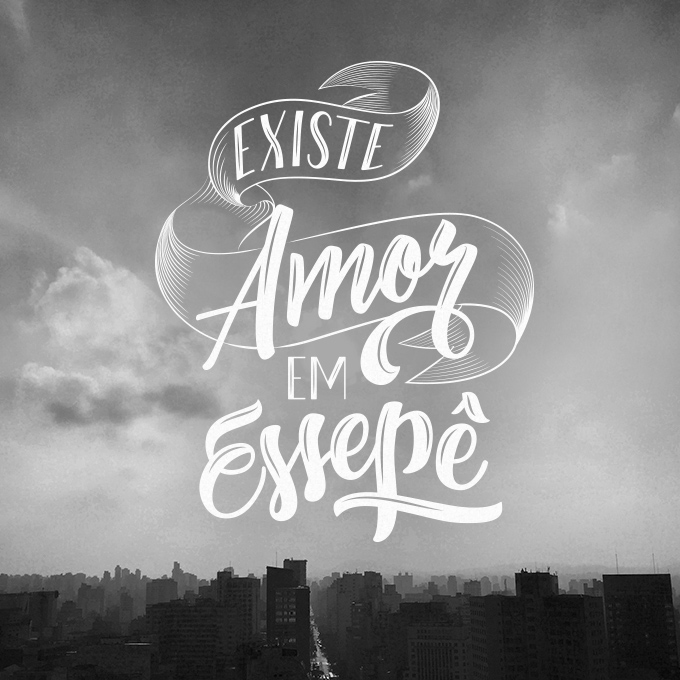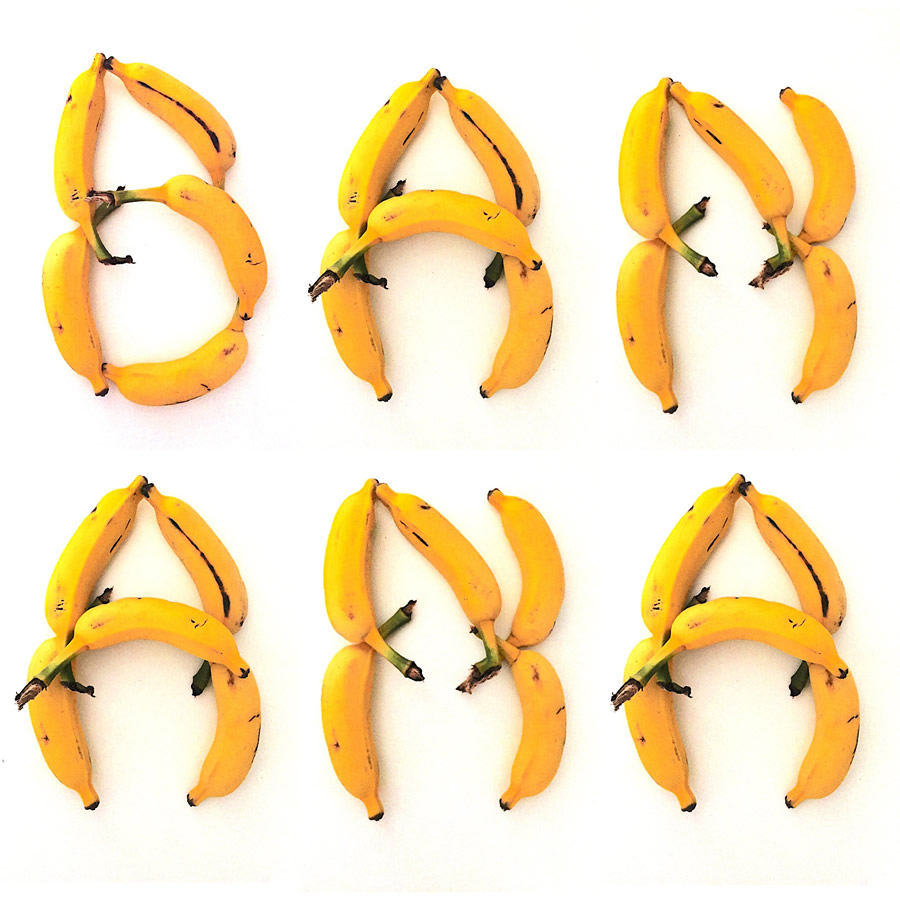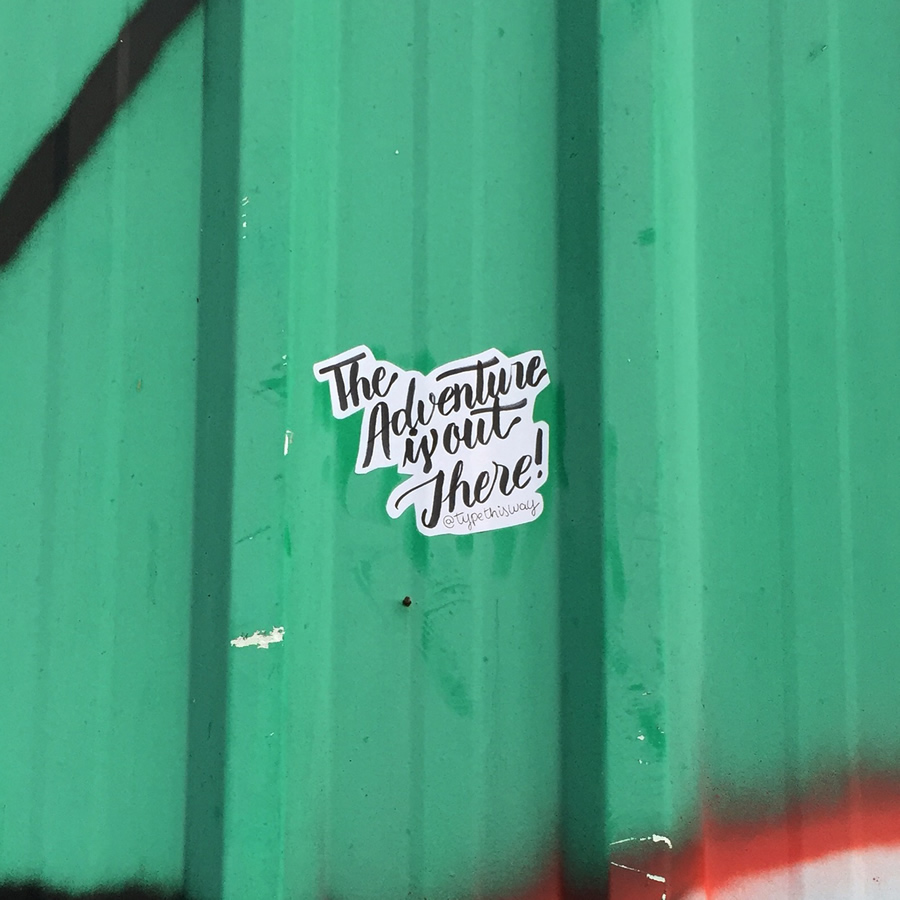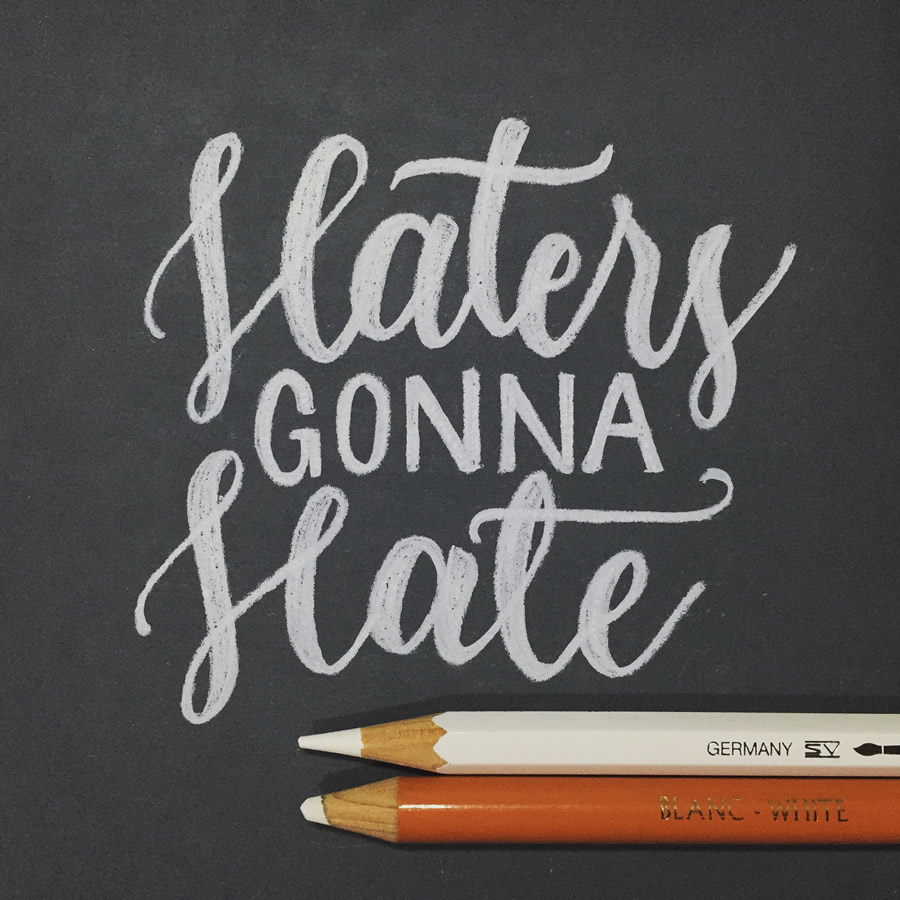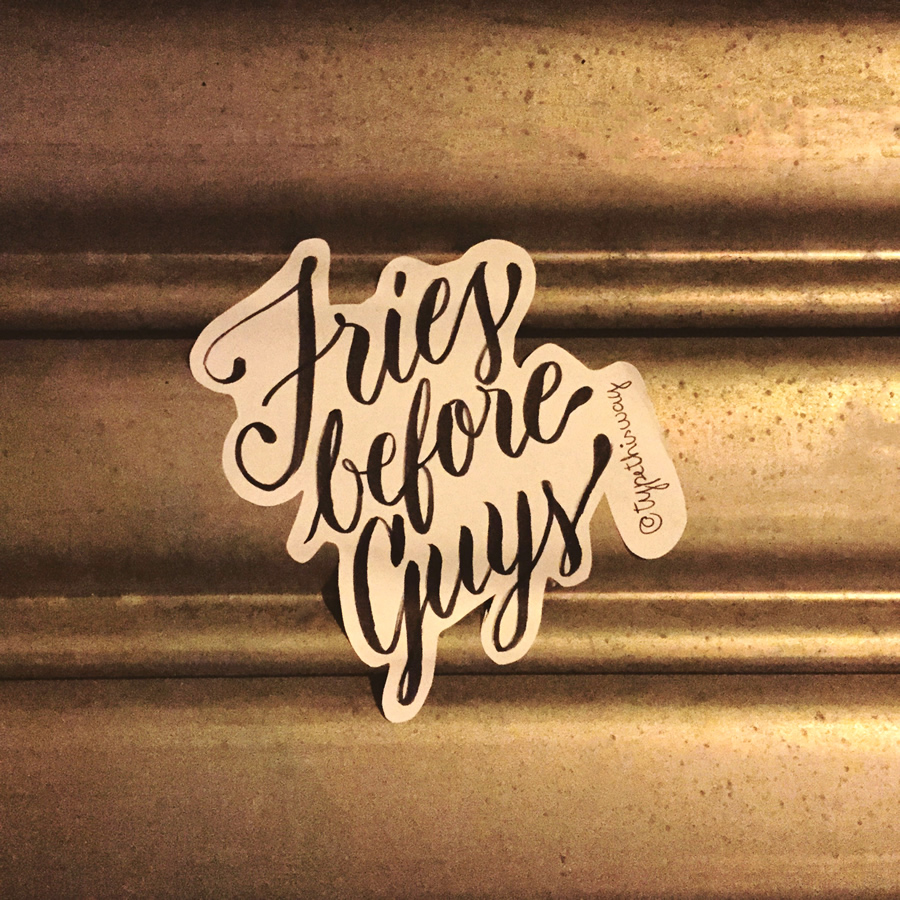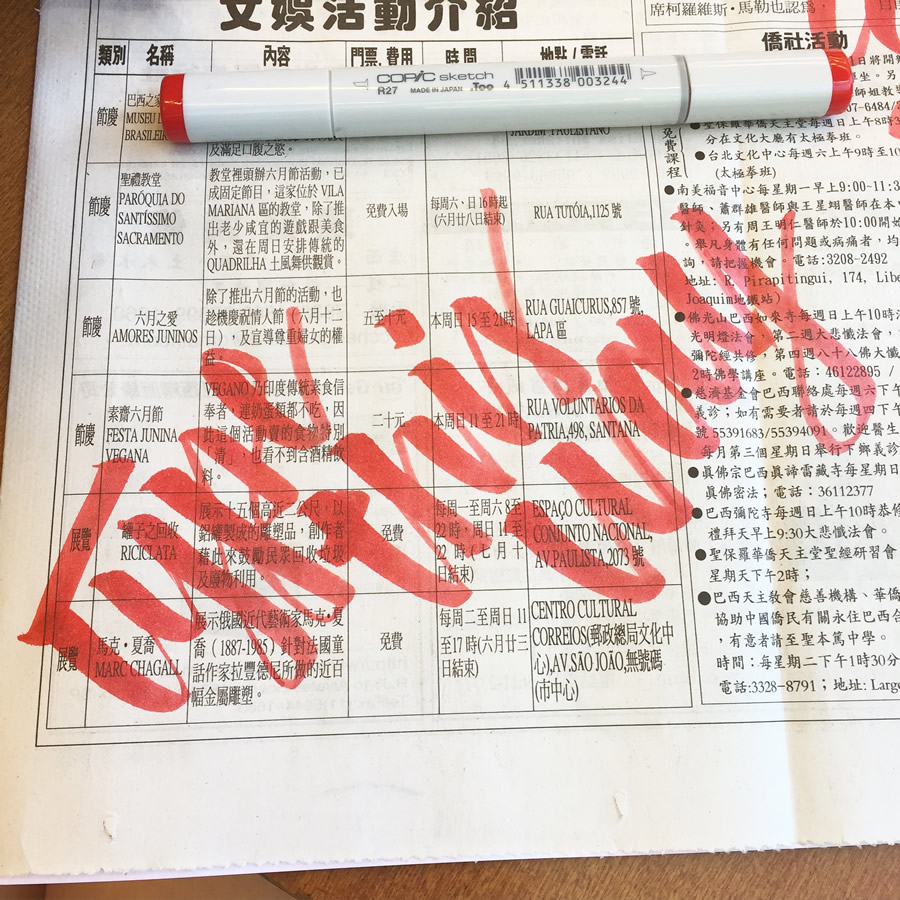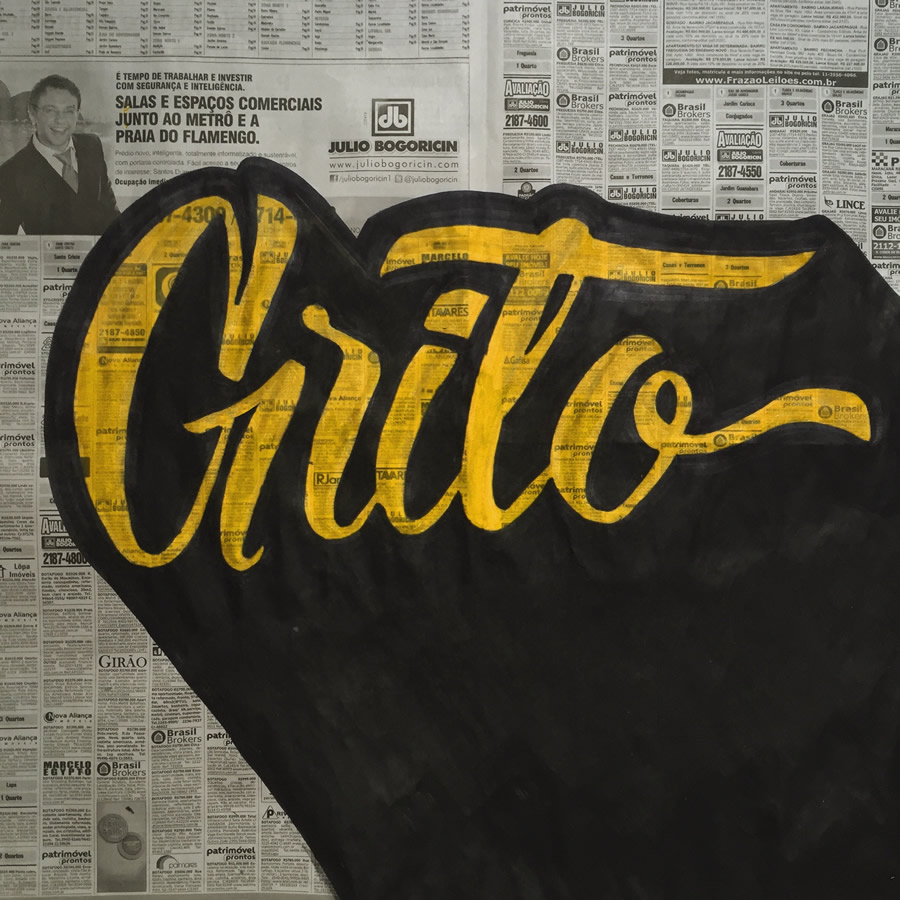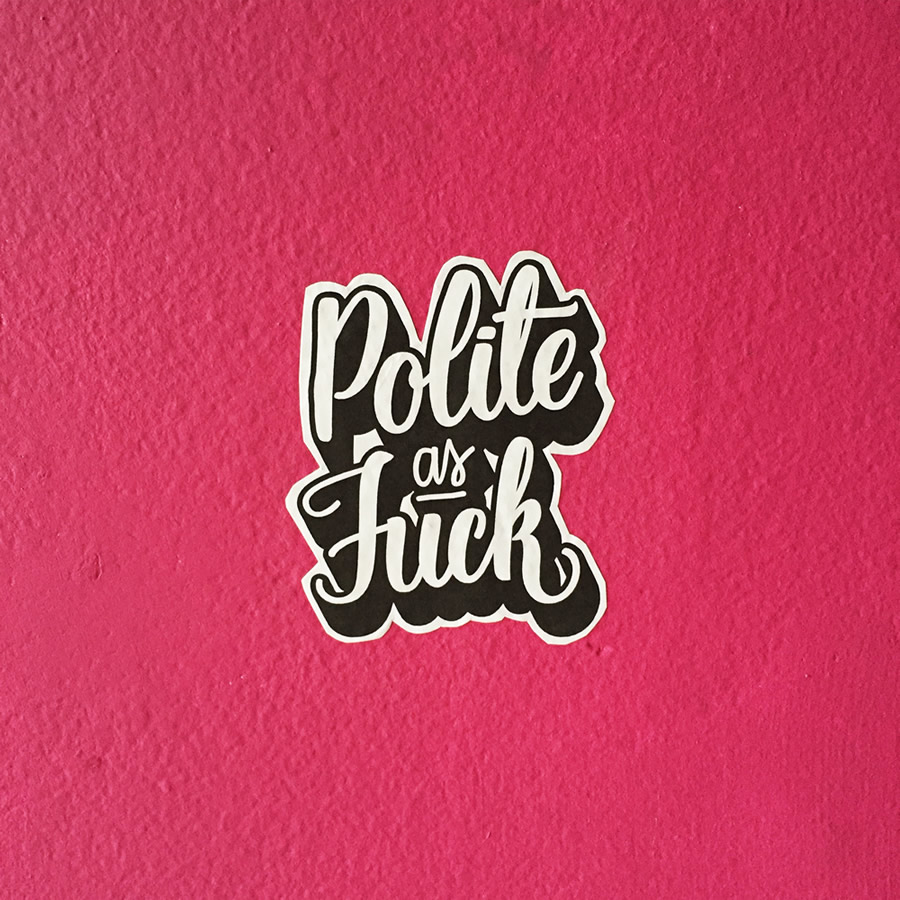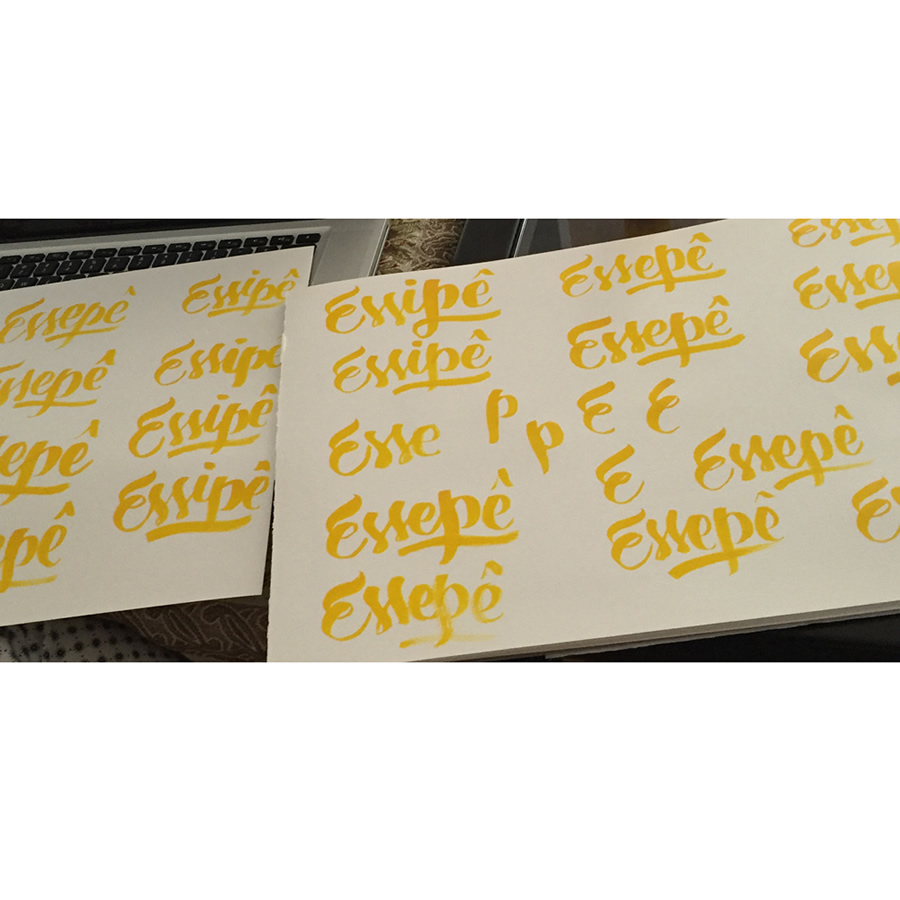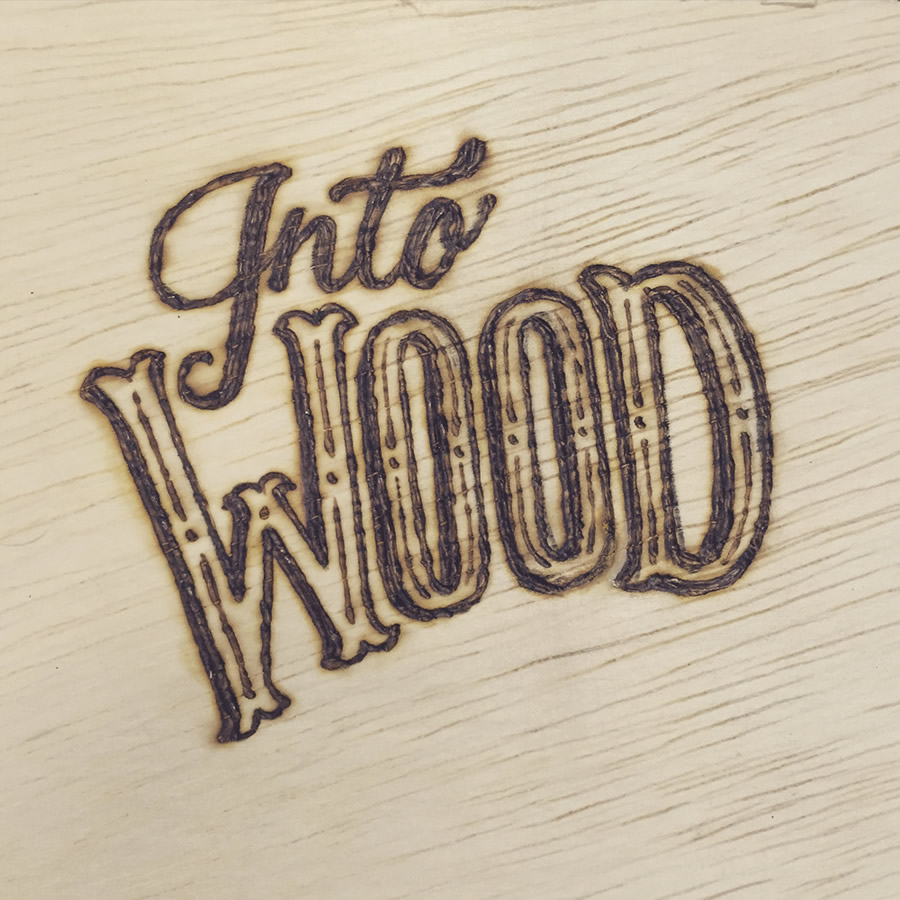
Queremos dar espaço para todas as pessoas talentosas de nosso país, por isso, convidamos a Fernanda Schlickmann, que trabalha com tipografia e tem um instagram muito legal, conheça Fernanda e suas criações.
Fernanda Schlickmann, 23 anos, nascida em Rondônia, de família sulista, e crescida Brasil à fora. Mudei algumas vezes e acho que isso fez enriquecer ainda mais minha bagagem cultural. Atualmente moro no Rio de Janeiro, há quase 7 anos, e foi onde descobri minha paixão por design e, mais recentemente, por lettering e caligrafia.
Cursando o 8º período de Design Gráfico na UFRJ, a quase um passo de me formar, se tudo der certo e se as greves deixarem!
Sempre fui apaixonada por letras e, por gostar de desenhar desde criança, senti que poderia arriscar desenhá-las também. Foi então, no 4º período da faculdade, que eu resolvi puxar uma matéria de Tipografia e aí me apaixonei perdidamente. Passei a pesquisar mais e a ter contato com amigos que trabalham com isso há algum tempo e a conhecer materiais e testá-los. Também tive a oportunidade de trabalhar na Plau, um escritório excelente de type, aqui do Rio, que está a todo vapor, onde aprendi com Rodrigo Saiani sobre técnicas, de como usar os materiais, organizar ideias e também vetorizá-las. O Rodrigo foi praticamente um professor particular de type, além de outras pessoas incríveis que tive a oportunidade de trabalhar nesta mesma empresa e conhecer outras ótimas por tabela.
Também busco inspiração no trabalho de vários designers brasileiros, em especial, Cláudio Gil, porque tive a oportunidade de participar de um de seus workshops em um evento regional de Design, o R Geração, em abril de 2014, e por fazer parte da comissão organizadora, tive um contato maior. O pessoal do Criatipos também me ajuda com as ideias bacanas que eles têm, piro a cabeça com tantos projetos incríveis. O Tipocali também é outra fonte de inspiração bem forte. Claro que tem os gringos que ajudam muito também, mas acredito que temos uma galera excelente aqui no Brasil, e acho que por mais que tenhamos inspirações vindas de fora, deveríamos valorizar mais o que andamos produzindo aqui dentro e dizer pro mundo que a gente também tem peso!
Atualmente estou arriscando e colocando minha cara na janela. Até então, o lettering e a caligrafia eram apenas um passatempo e um jeito de soltar minhas ideias. Muitos amigos insistiram para que eu postasse esses experimentos de lettering/tipografia, e resolvi criar um projeto pessoal. Fiz um Instagram para ajudar, o Type This Way (@typethisway), dica dada por um amigo, fazendo referência à música “Walk This Way” do RUN-DMC. Nele, eu posto meus experimentos com stickers, vetores, usando pirógrafo, madeira, lixa e até comida, sem exagerar nas postagens por dia, e sem ter que usar meu perfil pessoal. Assim, quem realmente se interessar, pode seguir sem se incomodar.
Os feedbacks começaram a vir e eu fui tomando um gosto maior pela ideia e comecei a ousar mais na maneira de realiza-los. Venho explorando várias superfícies e vários materiais diferentes, e está sendo ótimo! Me sinto muito mais criativa e disposta para pensar em coisas novas.
A meta agora é aprofundar o conhecimento através de cursos de caligrafia (flat e brush pen) para melhorar ainda mais minhas técnicas e ter mais segurança para postá-las sem medo.
Ainda me considero amadora e quero dominar mais técnicas, pois ainda estou no “you know nothing, Fê Snow”.